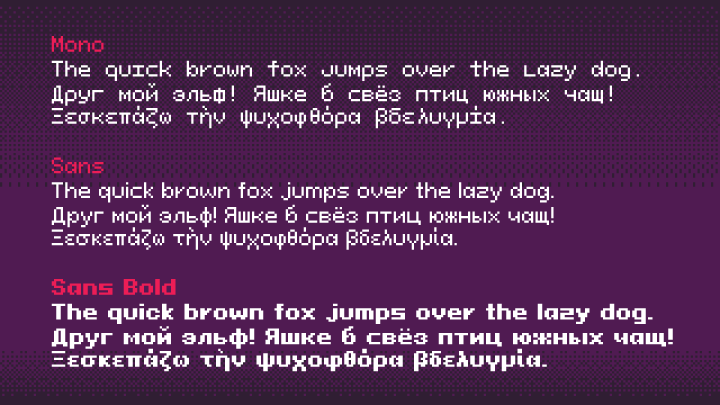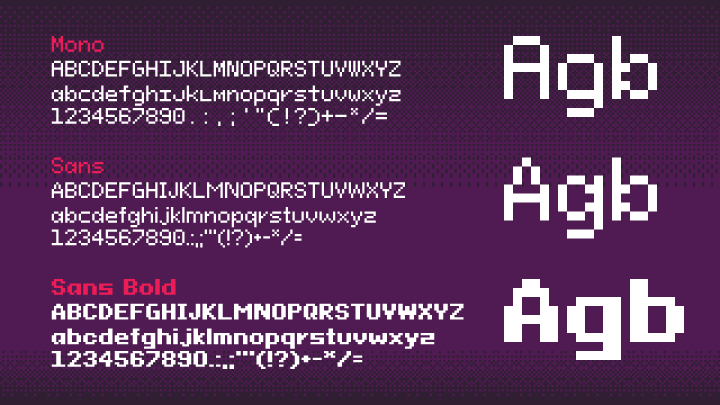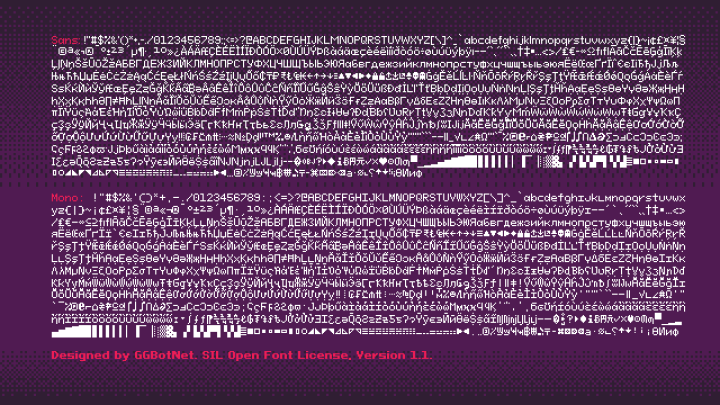
135种支持语言的Pixeloid字体素材,字体包含 3 种样式(等宽、无衬线、粗体无衬线)和 1141 个字形。
支持 135 种语言
南非荷兰语、阿赫姆语、阿肯语、阿尔巴尼亚语、阿斯图里亚斯语、阿苏语、巴萨语、巴斯克语、白俄罗斯语、本巴语、贝纳语、波斯尼亚语、布列塔尼语、保加利亚语、加泰罗尼亚语、车臣语、奇加语、科隆语、康沃尔语、克罗地亚语、捷克语、丹麦语、杜阿拉语、荷兰语、Embu、英语、世界语、爱沙尼亚语、埃威语、埃旺多语、法罗语、菲律宾语、芬兰语、法语、弗留利语、富拉语、加利西亚语、甘达语、德语、希腊语、古西语、夏威夷语、匈牙利语、伊博语、伊纳里萨米语、印度尼西亚语、爱尔兰语、意大利语、Jola-Fonyi、Kabuverdianu、卡拜勒语、卡拉利苏特语、卡伦金语、坎巴语、基库尤语、基尼亚卢旺达语、科伊拉基尼语、科伊拉博罗森尼语、拉科塔语、兰吉语、拉脱维亚语、林加拉语、立陶宛语、下索布语、卢巴-加丹加语、洛语、卢森堡语、卢亚语、马其顿语、马查梅语、马库瓦-梅托语、马孔德语、马达加斯加语、马耳他语、马恩岛语、马赛语、梅鲁语、梅塔语、莫里森语、纳马语、恩吉姆布恩语、恩贡巴语、北恩德贝莱语、北萨米语、挪威博克马尔语、挪威尼诺斯克语、努尔语、尼亚科莱语、奥罗莫语、奥塞梯语、波兰语、葡萄牙语、普鲁士语、克丘亚语、罗马尼亚语、罗曼什语、Rombo、伦迪语、俄语、鲁瓦语、桑布鲁语、桑戈语、桑古语、苏格兰盖尔语、塞纳语、塞尔维亚语、香巴拉语、绍纳语、斯洛伐克语、索加语、索马里语、西班牙语、斯瓦希里语、瑞典语、瑞士德语、塔切尔希特语、泰塔语、塔萨瓦克语、特索语、汤加语、土耳其语、乌克兰语、上索布语、乌兹别克语、乌兹别克语(拉丁语)、瓦伊语、沃拉普克语、文乔语、瓦尔泽语、威尔士语、西弗里斯兰语、扬本语、约鲁巴语、扎尔马语、祖鲁语。